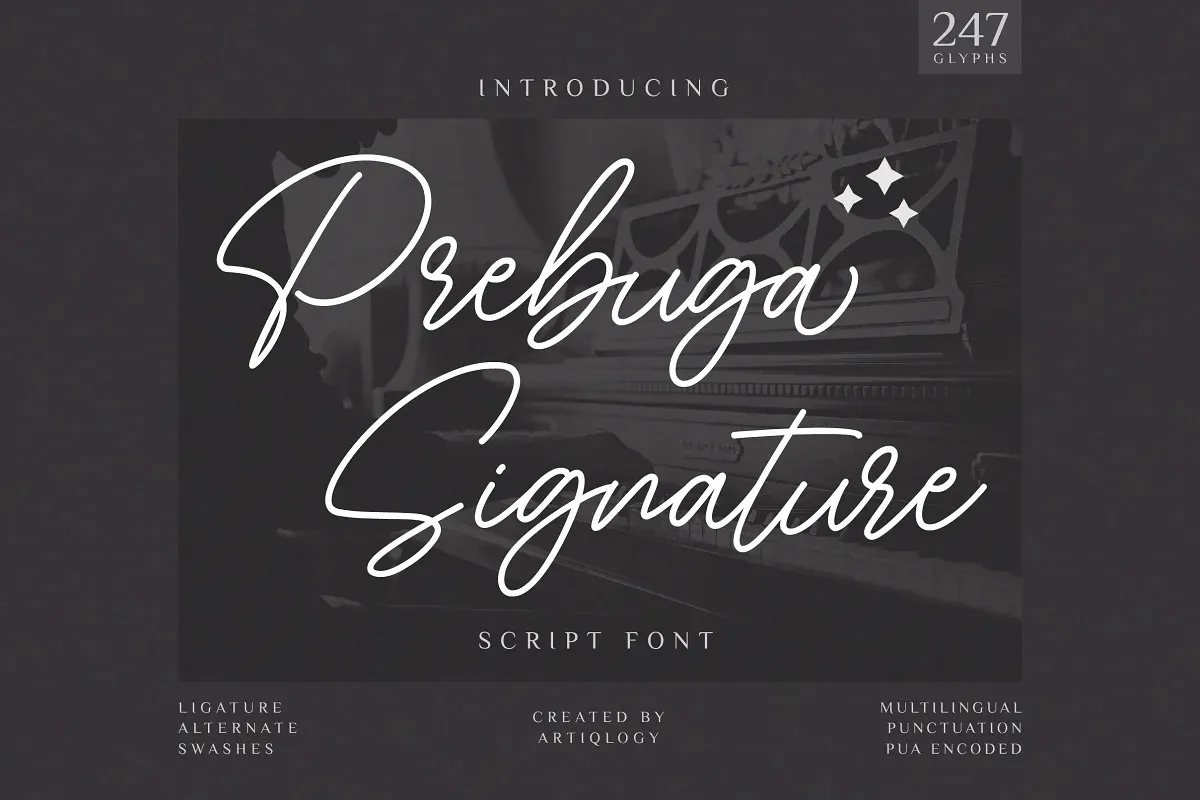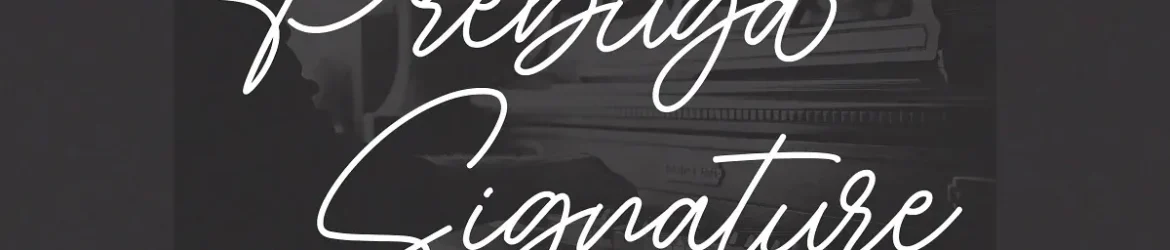
A Prebuga Signature Font é uma tipografia criada para surpreender com seu estilo elegante e autêntico. Este tipo de letra é perfeito para quem busca uma mistura única de naturalidade, artesanato e clareza no design. Com traços sólidos e um traçado único que oferece uma versão alternativa do minúsculo e ligaturas, a Prebuga Signature Font permite criar textos impecáveis. É perfeita para aplicar em desde cartões de convite de casamento até postagens de mídia social chamativas. Essa fonte é ideal para quem busca um toque especial e criativo no seu trabalho visual. Aprenda a apreciar seu charme inigualável através da Prebuga Signature Font, uma opção de tipografia perfeita para designers que buscam dar vida ao design com um estilo autêntico e singular.